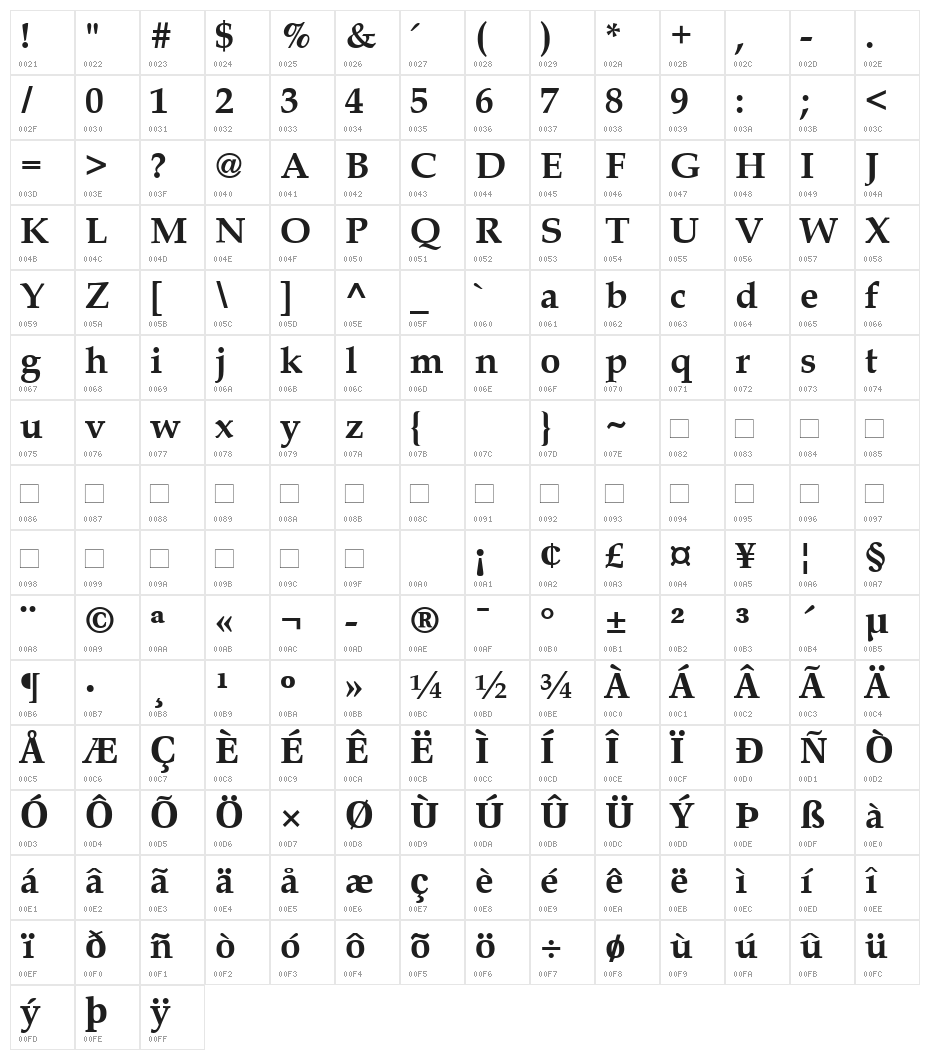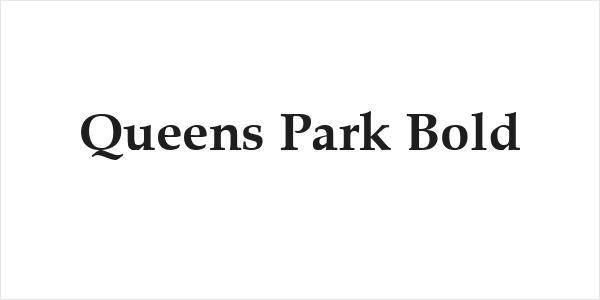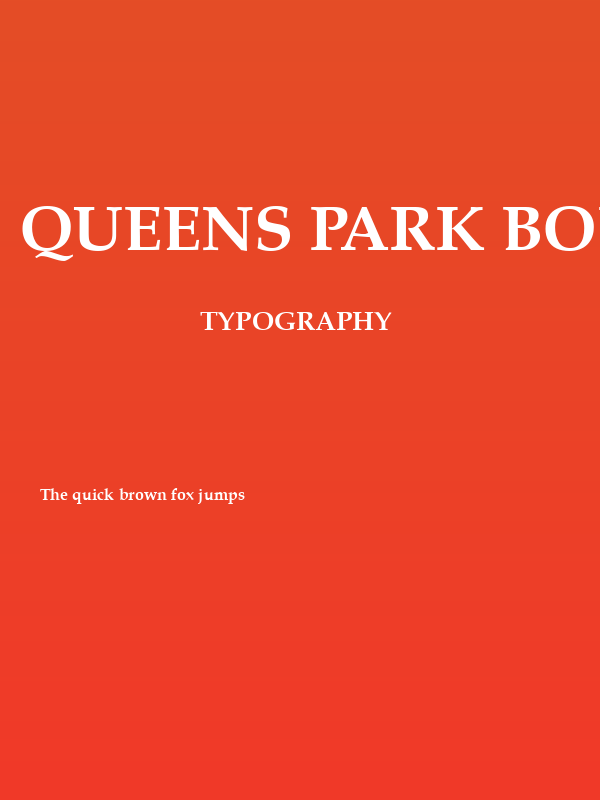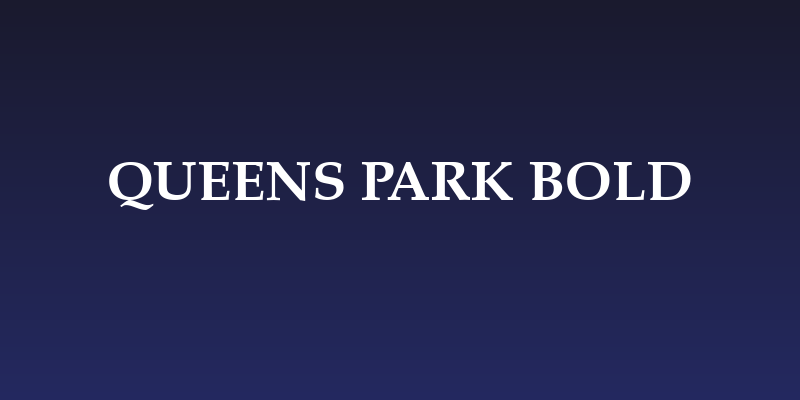
Queens Park Bold Font
| Projetos propostos | Ideal for editorial design, book covers, formal invitations, and branding projects that require a touch of elegance and tradition. |